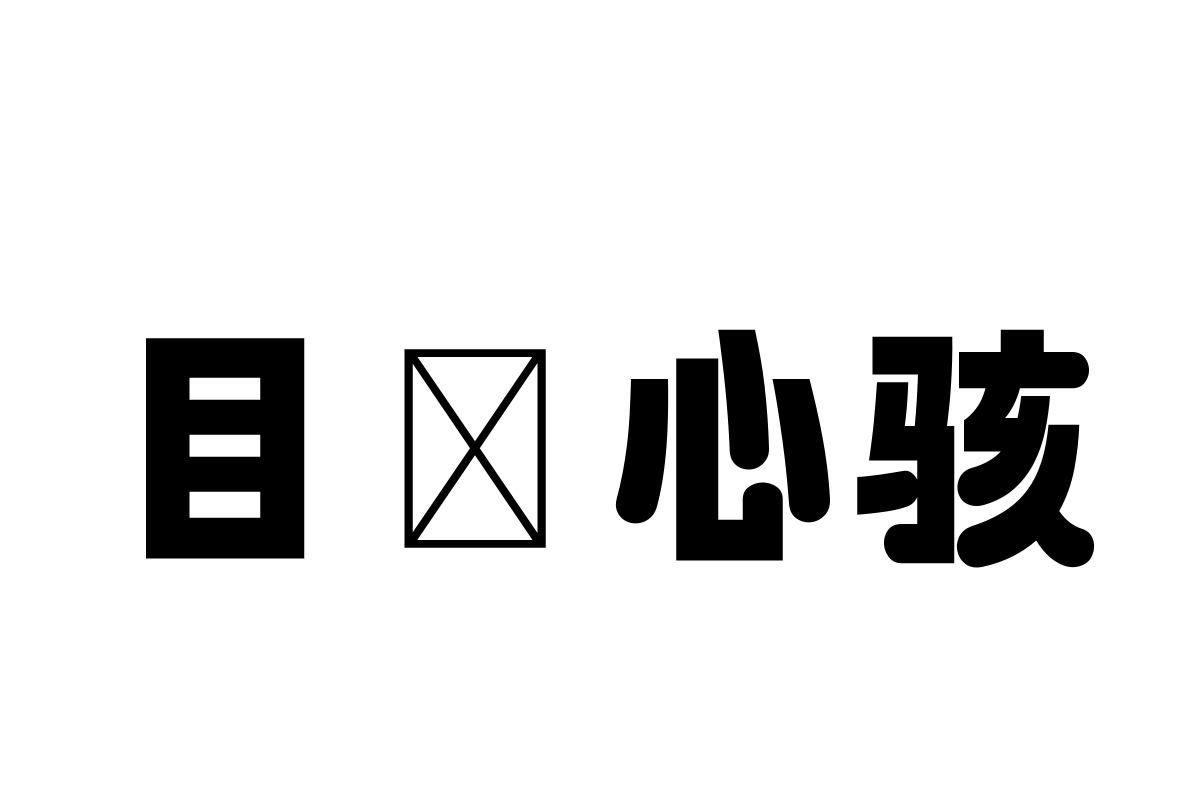
汉仪懒圆圆是一款免费商用的中文简体字体,由汉仪字库出品。该字体具有圆润可爱的风格,笔画流畅自然,适合用于儿童、卡通、可爱等场景的文字设计。
汉仪懒圆圆字体特点:
1. 字形圆润可爱,线条流畅自然,易于阅读和识别。
2. 适用于儿童、卡通、可爱等场景的文字设计,能够营造出温馨、可爱的氛围。
4. 支持多种中文简体字号,包括常规、小标宋、大标宋、细黑、粗黑等多种字号,满足不同场景的需求。
汉仪懒圆圆字体广泛应用于广告设计、包装设计、书籍封面、杂志、贺卡、海报、宣传单页等领域,为设计师提供丰富的创意灵感和便捷的设计工具。